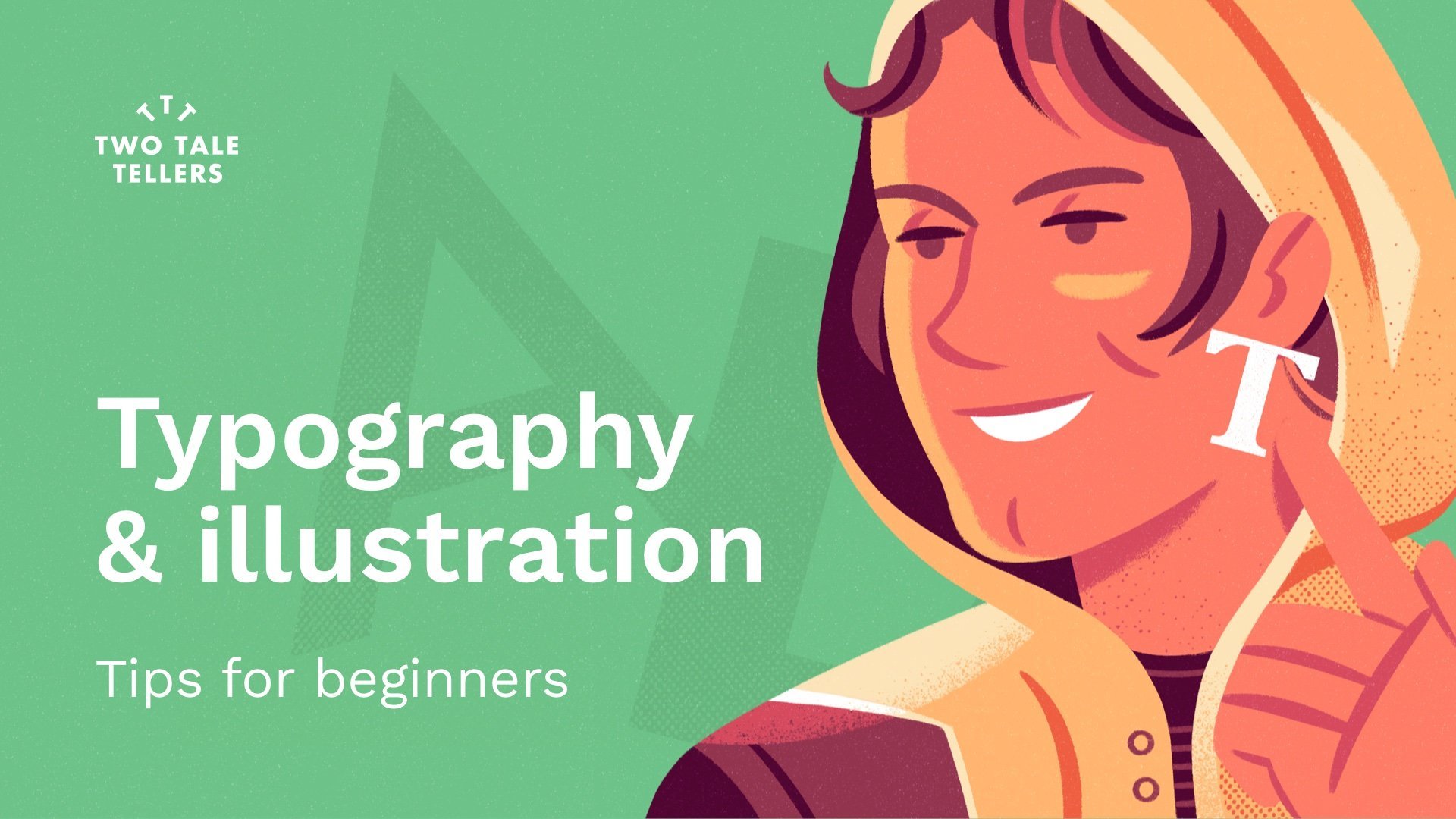
Typographie et illustration : conseils pour les débutants
Avez-vous déjà besoin d'intégrer la typographie dans vos illustrations sans vous sentir exactement celles à choisir ou comment l'utiliser naturellement dans votre travail ? Vous avez été curieux par rapport aux possibilités non seulement fonctionnes, mais aussi en plastique et en matière d'esthétique de typographie ?
Comment les jouer avec la perspective d'un illustrateur ou d'un artiste ? Vous avez vous ressenti un peu intimidé, car il est complexe et en théorie, il est orienté à la conception de graphiques ? Ce cours est pour vous.
Ce est et n'est pas ce
Il ne s'agit pas d'un cours de conception graphique ou typographiques, mais vous en apprendrez un peu plus sur la typographie, comment l'utiliser dans la pratique et en intuition, comment l'intégrer dans votre travail régulier en tant tant qu'illustrateur et comment is dans une perspective graphique.
Ce que vous apprendrez
à la fin de ce cours, vous aurez quelques notions pratiques de la typographie et de nouveaux outils créatifs. Et l'espoir n'hésitez pas à améliorer votre portfolio, vous pouvez relever quelques illustrations nouvelles et intéressantes.
Ce cours est particulièrement s'adresse à :
Illustrateurs qui ont intérêt à apprendre à utiliser la typographie dans leur travail, il est entièrement ouvert à toute créative qui possède un intérêt à la typographie ou à l'illustration.
1. Introduction: Avez-vous déjà eu besoin d'intégrer la topographie dans votre travail sans savoir exactement lequel choisir et comment l'utiliser naturellement dans votre travail, avez-vous été curieux des possibilités, non seulement fonctionnelles mais aussi plastiques esthétiques de typographie. Comment jouer avec eux du point de vue d'un Illustrateur ou d'un artiste, avez-vous été quelque peu intimidé par lui parce que c'est complexe et en théorie orienté vers les graphistes. Dans ce cas, c'est votre classe. Mon nom est le rôle et je suis illustrateur et designer. J' ai travaillé pour des contenus éditoriaux, des marques et des produits, des projets narratifs interactifs , des jeux vidéo et tout support dans lequel des images, des pupilles ou des interactions sont combinées pour raconter Soyouz. Très souvent, je m'adresse à mon travail d'illustrateur. Ma connaissance de la topographie s'obtient après 20 ans travail dans des domaines tels que l'entité d'aide visuelle ou la conception d'interface. Et croyez-moi, ça peut être un excellent outil pour un illustrateur. Ce n'est pas un verre de design graphique ou typographique, mais dans celui-ci, vous en apprendrez plus sur la typographie dans la façon de l'utiliser d'une manière pratique et intuitive. Comment l'intégrer dans votre travail régulier en tant qu' illustrateur et comment l'utiliser d'un point de vue plus graphique. Commencera par donner quelques conseils essentiels pour choisir le bon téléphone en fonction du contexte. D' une manière pratique et non académique. Nous parlerons de différentes méthodes pour l'intégrer visuellement dans votre travail afin qu'il ne semble pas détacher de votre façon de lancer. Ensuite, nous allons proposer trois exercices avec un petit projet associé à chacun que vous pouvez choisir de faire. Tous sont concentrés sur celui qui vous intéresse le plus. Ces exercices vont de l'intégration de textes de base à l'utilisation de la topographie comme élément visuel clé dans vos illustrations. Je vais vous montrer mes propres exemples et ceux d'autres illustrateurs et société Alec que vous créez mes propres projets autour des exercices proposés. Enfin, je vais vous donner quelques références sur l'endroit où trouver des polices de qualité complètement gratuites ou très abordables et quelques conseils finaux. À la fin de ce cours, vous aurez des notions pratiques de typographie, nouveaux outils créatifs et, espérons-le, de nouvelles illustrations intéressantes qui vous permettront d'élever votre portfolio. Pour prendre la classe, vous avez besoin de votre créativité. Les moyens que vous seriez juste de faire des croquis et vos outils habituels tant qu'ils vous permettent de manipuler la topographie, moins d'une manière simple. Illustrator, Photoshop, procréer, Affinity Designer, chacun d'entre eux fonctionnera pour vous. Ce cours s'adresse spécifiquement aux illustrateurs qui veulent apprendre à utiliser la typographie dans leur travail. Mais est complètement ouvert à toute personne créative ayant un intérêt pour la typographie ou l'illustration. Êtes-vous prêt pour ça ? Je suis allé te chercher dans la vidéo suivante. Commençons. 2. Votre projet de cours: Cette classe est divisée en trois exercices qui représentent trois propositions pour explorer la topographie. Pour illustrer chacun des exercices, je vais créer un projet personnel. Je vous invite à développer vos propres projets autour du verre. En tant qu'étudiant, vous pouvez choisir de produire un projet pour son exercice. Oui, choisissez un ou deux, ou même faites plusieurs illustrations pour chaque exercice. C' est complètement à vous de décider. Dans notre exemple de projet, vous pouvez voir comment nous avons présenté nos propositions pour chaque exercice, décrivant leur processus créatif derrière eux, les polices utilisées dans un petit contexte autour de la solution. Vous pouvez utiliser nos projets comme exemple pour structurer les vôtres. Mais bien sûr, vous avez une totale liberté de montrer avec une supernova. Donc, avec le projet clarifié, commençons par le verre et le premier exercice, accompagné de divers conseils, je vous invite à développer vos projets au fur et à mesure que la classe progresse. Ça commence. 3. Exercice 1 - Intégration du texte: Nous commencerons par l'un des contextes les plus élémentaires quand il s'agit de la dorothie appliquée à l'illustration, c'est-à-dire la présence de la topographie dans un texte. Ce texte peut être mordre un morceau de journal, un panneau dans une rue, un dessin typographique sur un t-shirt de personnage, textes sur une carte illustrée, etc. Voyons quelques exemples. Parfois, ces textes peuvent avoir une présence très limitée dans votre travail. Comme dans cette illustration faite pour un article sur Medium. Comme vous pouvez le voir, certains petits textes, tels que la plaque d'immatriculation, sont parfaitement intégrés dans l'illustration. Et malgré sa subtilité, ils fournissent la crédibilité nécessaire à ce petit composant visuel mal traité pourrait avoir un impact vraiment négatif sur l'ensemble. Dans cette autre illustration, nous adaptons la police au contexte lié à protéine avec la police Meghan ou égyptienne qui s'adapte au flux du dessin. Dans l'autre, nous pouvons voir comment la topographie s'adapte à la construction de l'illustration, s'y intégrant et en délivrant un message en même temps, ce qui renforce le résultat général. Dans cette belle illustration de la grande carte de l'artiste, nous pouvons voir comment il a intégré ce panneau dans le bâtiment avec un choix typographique intelligent et une finition précise pour son contexte. Steve offre comme d'innombrables exemples sur la façon intégrer professionnellement la topographie dans son travail d'illustrateur en utilisant pratiquement toutes les méthodes d'intégration décrites dans la vidéo 5 de son verre. Eh bien, je vous ai parlé de la façon d'utiliser le type d'une manière qui ne semble pas hors de propos compte tenu de votre style personnel. Souvent, le peu de soin dans le choix de la police et le manque d'intégration visuelle dans l'illustration, même dans des contextes professionnels, rendent les résultats quelque peu maladroits et ne disent pas grand-chose sur la garderie pour la finition de sortie pour cette raison, avant de commencer notre premier projet, nous allons voir quelques conseils sur le choix et utilisation de la typographie sans entrer dans trop de détails techniques. L' indention est de faciliter l'utilisation de ces ressources pour les personnes qui n'ont pas une formation spécifique en design graphique générant malgré cela, un bon résultat final, partons avec nos premiers pas, qui seront très utile dans tous les exercices de la classe. 4. Exercice 1 - Conseils de choix typographiques: Choisir la police correcte représente probablement 70 % du travail. Le choix de la police est quelque chose de vraiment subtil et nécessite une connaissance de jugement. Comme d'habitude, plus nous en savons sur la typographie, il est facile de la subvertir. Utilisez un graphiste professionnel expérimenté à bonne maîtrise utiliser une base de données apparemment inappropriée pour un contexte. Mais partons de la prémisse que nous n'avons pas une formation spécifique et ignorer que voir quelques cassettes à la loi plus rapidement par le brouillard est notre choix. Considérons au moins trois aspects. Un, contexte général à la nécessité fonctionnelle, trois propriétés esthétiques. Regardons quelques exemples et analysons chacun des points qui y sont mentionnés. Revenons à l'illustration précédente de Steve Scott. Pensons à l'éclatement du contexte général. Nous parlons d'un hôtel élégant et sophistiqué avec une touche traditionnelle. Il semble tiré d'il y a quelques décennies. Logiquement, cette situation n'exige pas une déphase punk informelle, jeune et audacieuse, bien au contraire. Elle exige une certaine souveraineté et une certaine distinction. En étant conscients de cela, nous aurons commencé à nous concentrer sur notre choix. Besoins fonctionnels dans ce cas, R est dominant. Nous parlons d'un grand panneau visible et nous avons seulement besoin du nom de l'hôtel pour être lisible. Et même si elle n'était pas totalement lisible, cela n'affecterait pas la perception générale de l'illustration. Enfin, considérons les propriétés esthétiques. Quel type de police exige-t-elle une telle situation ? Une police de caractères extraterrestre aurait pu être un choix approprié. Mais ici, Steve utilise un friand avec quelques souvenirs historiques contemporains qui offre le bon degré entre modernité et tradition pour contraster avec la main, les finissent par fournir une belle finition finale. Passons à une autre affaire. Ici, nous voyons comment la lame de licence en arrière-plan reçoit toute la tension typographique dans l'illustration. Dans ce cas, un contexte général et un besoin fonctionnel. Clair. Nous parlons d'une plaque d'immatriculation, et la grande majorité des plaques d'immatriculation dans le monde ont une apparence similaire en termes de topographie. La raison est simple. Nous parlons généralement de la police OCR. C' est le signe de la reconnaissance optique des caractères. Clairement lisible, reconnaissable et scannable, sorte qu'il est impossible de confondre certains personnages avec d'autres. Même si cette police n'est pas celle utilisée dans les plaques d'immatriculation. Il répond à toutes les exigences en termes de contexte, de fonction et d'esthétique, sorte qu'il est perçu comme crédible que leur biographie pour New York est beaucoup plus libre et fournit simplement un contraste avec le numéro de plaque d'immatriculation. Le contraste qui est produit non seulement en termes de style, mais aussi en échelle, poids et couleur, séparant clairement les deux chauves-souris. Et comme un k supplémentaire, nous pouvons étudier comment dans ce jeu vidéo que j'ai aidé à concevoir les choix typographiques, réagissant aux points décrits avec une relation esthétique évidente. Triple Squad était un jeu très simple et puissant. Tous les éléments du jeu où l'édition minimaliste et compacte ou coeur et la police monospace à la recherche mécanique ont été utilisés pour la construction du logo et du texte de soutien. Les véhicules du jeu semblaient avoir été conçus à côté de la police. Il y a une esthétique ou une relation évidente. Fonctionnellement, Arete a été relégué à court un texte d'impact. Enfin, nous pourrions considérer le budget comme le quatrième à examiner. Avoir le budget à acheter. typographie peut multiplier vos possibilités, bien qu'elle ouvre également un immense espace. limiter aux polices accessibles vous aidera à vous concentrer sur les options disponibles, même si vous devrez peut-être sacrifier l'accès à de meilleures alternatives. Rappelons-nous encore une fois, soyons logiques compte tenu du contexte général. Pesons le besoin fonctionnel de cette police à quel point C'est Bertha qui crée nécessaire. Examinons ce que nous voulons que cette police de caractères exprime ? Autrefois sérieux, gentillesse, fraîcheur, parallèles ascétiques avec le reste des éléments de l'illustration, etcetera. Voici quelques conseils généraux pour vous guider dans ce premier choix. Nous en verrons plus à ce sujet dans l'exemple de projet. Mais une fois ce choix fait, il est temps d'utiliser cette RFI dipôle dans l'illustration. Comment l'intègrons-nous ? Comment l'utiliser de telle sorte qu'il ne se sent pas d'un monde différent de votre illustration ? Voyez quelques conseils pratiques dans notre prochaine vidéo. 5. Exercice 1 - Conseils d'intégration: Si votre travail est formellement simple, plat et principalement vectoriel, vous n'aurez pas trop de problèmes puisque la finition Buffett de la topographie s'adaptera parfaitement à vos illustrations. Si d'un autre côté, vous avez un style plus organique, cette topographie pourrait sembler hors contexte comme un mais quelque chose de super-imposé sur le net. Et cela appartient à un monde différent, peu intégré. Je vais donc recommander trois méthodes différentes pour faire l'intégration. Un, la manipulation numérique, au redessin, et trois, l'imitation. Laissez expliquer très rapidement ce qu'ils consistent en utilisant quelques exemples. Manipulation numérique. C' est l'une des options, sont utilisés le plus dans mon travail, mais il nécessite une compétence à manipuler numériquement la topographie. L' intention est de déformer ou d'éroder numériquement les lettres afin que nous obtenions une finition artificielle proche ou au moins compatible avec nos illustrations. C' est exactement ce que j'ai fait dans cette illustration qui parle nomades et des gens qui ont littéralement porté leur maison dans leurs circuits. La présence de textes est subtile et peu pertinente dans l'illustration, mais son intégration est adéquate. Regardons la finition de la police de caractères. La même chose se produit dans ces autres illustrations. Nous voyons que la topographie, malgré le maintien de toutes ses caractéristiques d'origine, est légèrement déformée de sorte qu'elle s'intègre plus naturellement. Dans mon exemple de projet. Dans la vidéo suivante, je vais vous montrer comment nous pouvons faire ce type de modifications à l'aide de Photoshop. Regardons la deuxième possibilité lors de l'intégration de la topographie, du redessin. Il consiste littéralement à utiliser la police correspondante dans votre composition. Et il suffit de le redessiner en utilisant vos brosses et finitions habituelles. Comme vous pouvez le voir dans ces illustrations que j'ai faites il y a quelques mois pour le jeu vidéo, Threadless Trail of blood. Le texte semble être une typographie simple disposée sur l'illustration. Mais si on se rapproche de leur détail, on verra que la finition des lettres est exactement la même que le reste de l'illustration avec toutes ses imperfections. Essentiellement, notre main a tracé le design parfait d'une police à la main. Nous pouvons voir le même processus dans la topographie organiser sur le T-shirt de ce personnage du même jeu vidéo. Ou sur la dernière petite note dans cette histoire officielle courte et structurée. Le résultat est que nous conservons toutes les vertus et les caractéristiques de la police d'origine, mais légèrement subverties par notre propre processus de travail créant une intégration remarquable. Évidemment, cette option nécessite beaucoup d'efforts et elle n'est recommandée que pour de petites interventions typographiques. Voyons une autre façon d'intégrer la topographie, très utilisée par les illustrateurs et l'imitation. Nous avons une alternative que nous pourrions déjà envisager le lettrage, car cela implique d'imiter manuellement l'apparence d'une police. La différence avec le redessin est que, dans ce cas, nous n'avons pas besoin d'avoir une référence pour en tirer parti. Nous interprétons manuellement l'attribut d'une police en fonction de notre besoin. Généralement, le résultat finit par être une police de caractères qui s'est déjà éloignée de la référence d'origine, mais qui conserve largement son identité. Nous pouvons voir quelques exemples pourquoi matériel don Noter comment il imite une police condensée sans serif sans être reconnu comme personne en particulier. Vous dessinez essentiellement des lettres, donc celles-ci s'adaptent parfaitement à vos illustrations. Voici un exemple de Steve Scott ce qu'une police de caractères rappelle plusieurs polices similaires sans être réellement aucune, car elle imite l'aspect approximatif de la police ici nécessite. Alors rappelons-nous, le choix d'une police appropriée est une décision importante. Les deux. Donc E l'utilise correctement dans son contexte. Les aspects fonctionnels sont souvent au-dessus de l'esthétique, mais les cas brillants sont ceux qui établissent un juste équilibre entre les deux. Et l'utilisation originale et intéressante de la typographie peut devenir un élément identitaire important dans votre projet. Avec cette information entre nos mains, nous allons commencer à résoudre notre projet pour ce premier exercice. se voit dans la vidéo suivante. 6. Exercice 1 - Exemple de projet: Maintenant que nous avons le contexte complet de son exercice, je vais commencer par mon projet d'intégration typographique. Je vous invite à vous joindre à moi. Ce sera assez bref puisque nous allons nous concentrer sur la typographie en durée sur une illustration prête à l'emploi. Laissez-le commencer par un exemple très simple, qui peut nous aider à nous réchauffer puisque la police serait appliquée sans trop d'autres Asiatiques en perspective, va commencer à partir de cet exemple, une illustration secondaire pour un qui parle de l'importance des couvertures de livres. L' illustration fait allusion au fait que la couverture, en particulier dans les œuvres autopubliées, devrait parler de l'autre. Votre identité ou votre image personnelle devrait atteindre la couverture. Nous l'exprimons à travers un dessin dans lequel, euh, la couverture et la phase sont les mêmes. Maintenant, nous devons itérer en textes, titre et autres, bien que les deux soient très génériques. Donc on va résoudre ça avec mon roman et le nom et Smith. Maintenant, nous avons besoin d'un peu de contraste entre les deux textes. Et il y a plusieurs façons d'obtenir ce contraste. Cela peut être à travers une différence dans le poids du type, phase, la différence de taille, la différence, couleur, la différence de style, ou plusieurs de ces possibilités en même temps. Nous commencerons donc par expérimenter diverses combinaisons. Dans ce premier exemple, le contraste est quelque peu exagéré. Bien que le texte rappelle la machine à écrire monospace dans les polices, il est très mince et serait probablement perdu dans la conversation. D' autre part, le titre est un peu générique en termes de style. En inversant les styles, nous n'obtenons pas un résultat particulièrement intéressant. Essayons de changer la police du titre en une avec serif. Honnêtement, je l'aime mieux. Il a plus de caractère. Mais un contraste avec la police à espacement unique ne m'a pas convaincu. Rappelez-vous que nous n'avons pas besoin d'utiliser différents styles. J' utiliserai le même formulaire pour le nom init Alix et en respectant la différence de tailles. Pas mal. Peut-être si c'est classique. Ok. Retournons en arrière. Que diriez-vous d'utiliser une police sans serif ? majuscules avec un certain poids. Je l'aime, mais je pense que je vais envisager d'utiliser la même police pour les deux textes comme nous l'avons fait avec la police serif précédente. Je pense qu'il y a deux options sont certainement les plus intéressantes. Allons donc à Photoshop et je vais vous montrer comment nous appliquons ces fonds à l'illustration originale en utilisant la première méthode d'intégration décrite dans la vidéo précédente. N' oublions pas que le processus précédent est une version simplifiée et simple de ce qui serait un processus beaucoup plus organique et parfois rigoureux. Prenez le temps dont vous avez besoin pour étudier les possibilités. Une fois que nous sommes dans Photoshop, Nous allons commencer par entrer le texte nécessaire pour séparer les zones de texte pour être en mesure d'être manipulé indépendamment. Positionnera chaque zone de texte à peu près sur l'illustration. Ensuite, nous allons appliquer la couleur à chacun pour donner la palette de couleurs est un plus petit possible. Nous utiliserons l'un des verts pour le titre et le blanc pour le texte inférieur, qui contrastera suffisamment, changera la taille et le poids pour le rapprocher de l'aspect final que nous avons choisi dans notre étude précédente. Et après cela ferait pivoter les deux zones de texte 15 degrés, qui était un TLT utilisé pour faire pivoter le livre dans l'illustration. Et une fois qu'une décision est à nouveau ajustée, notre première proposition est présentée. Comme vous pouvez le voir, la finition imparfaite de l'illustration est différente de celle d'une police qui conserve son design parfait intact. Cela rend la topographie mal intégrée, évidemment superposée sur le dessin. Plus tard, nous appliquerons un ajustement. Évitez ce remplissage et améliorez l'intégration. Passons maintenant à notre deuxième proposition. L' utilisation de la police sans serif choisie précédemment appliquera la manière appropriée à chaque texte, positionnera chacun d'eux là où ils appartiennent. Dans le cas du nom de l'auteur, nous allons réduire sa taille et augmenter l'espace entre les caractères. Et le moyen facile de le faire est en sélectionnant les ponts et en appuyant sur l'option plus la flèche gauche ou droite pour l'augmenter ou la diminuer. Et avec cela, nous avons nos deux propositions, le temps de choisir. Comparons les deux. Bien que les deux semblent adéquats. Il me semble que dans ce cas, la police serif est un peu classique pour le style graphique de l'illustration. Et bien que cela puisse donner lieu à un contraste intéressant, je pense que dans ce cas, j'opterai pour une proposition moins contrastée. Après tout, la topographie est ici un élément complémentaire avec une décision prise il est temps d'améliorer l'intégration visuelle de la typographie. Pour ceux-ci, j'utiliserai Photoshop pour modifier les barons de la police. Tout d'abord, je vais sélectionner les deux textes et les transformer en un objet intelligent qui me permettra d'appliquer des effets sur la typographie de manière non destructive. L' une des choses qu'ils utilisent le plus dans ce cas est le filtre d'ondulation, qui est légèrement déforme les contours, les rendant moins parfaits sont plus organiques. Dans ce cas, il s'agit de jouer avec la taille et la quantité de défaut. Heureusement, faire une erreur ne sera pas un problème. Nous pouvons changer les paramètres autant que nous le voulons. Nous allons pour une taille plus petite, plus subtile, et une quantité d'effet plus faible. Si nous zoomons, nous pouvons voir comment la démographie semble être un peu plus proche de la fin de l'illustration. Peut-être que le défaut est invisible lors du zoom arrière. Donc nous allons forcer le social dans un peu plus. Nous allons éditer le petit filtre et changer les paramètres. Puisque l'illustration a une texture subtile ou appliquée, améliorera la sensation d'être imparfait textes imprimés en masquant le dx avec une certaine texture. Si vous regardez le détail, vous verrez à quel point le texte semble faire partie de l'illustration d'une manière naturelle. Observez un petit détail. ce moment, nous travaillons à la plus grande taille que celle que nous trouverons à utiliser. Nous allons donc copier le contenu du fichier. Nous allons le coller dans un autre document. Et nous allons réduire l'échelle à 50%. De cette façon, nous pouvons voir la finition finale jusqu'à la réduction de l'image. Beaucoup de détails qui peuvent sembler quelque peu artificiels sont devenus beaucoup plus naturels et il est difficile de savoir comment cette police a été appliquée pour paraître si bien intégrée. De cette façon, j'ai déjà intégré ces petits textes qui ont fini par faire partie de mes illustrations. D' une part, la police choisie semble appropriée à son contexte. L' intégration avec un léger autre angle de rationnement est assez crédible. La légère déformation pour éviter la finition mécanique des personnages ainsi qu'un effet de détresse ont contribué à l'intégrer sur l'illustration. Concernant les facteurs importants. Premièrement, un bon choix typographique basé sur les conseils que nous avons vus dans notre vidéo précédente plutôt qu'à un traitement et une intégration adaptés à la nature de votre travail. Et j'espère que de cette façon, ajouter un petit texte intégré sur vos illustrations sera un peu moins intimidant de la part de personne. Allez-y et préparez et partagez votre projet pour cet exercice. Si vous vous sentez particulièrement courageux, offrez-vous un défi intéressant, comme avoir à itérer un texte d' importance notable dans le contexte de votre illustration. Passons maintenant à un deuxième exercice. Cette fois beaucoup plus axé sur la valeur plastique de la typographie. 7. Exercice 2 - La typographie comme cadre visuel: Dans cet exercice simple et amusant, nous allons voir comment la typographie peut être utilisée à d'autres fins, plus proche de la conception graphique, l'objectif est que l'exercice vous inspire à faire plus de recherches sur la topographie et à l'utiliser dans un façon plastique. Nous choisirons un concept que nous sommes intéressés à représenter. Cela peut être un remplissage, une couleur, ce pays, un genre musical, tout ce qui peut être illustré et que nous pouvons identifier avec le mot. Ensuite, nous allons utiliser le type 4f0 pour créer un élément visuel pour encadrer notre illustration. Il peut s'agir d'une seule illustration ou d'une illustration pour chaque personnage unifié de façon spectaculaire. L' idée est que la topographie renforce le caractère du concept illustré. La chose la plus simple sera de voir un exemple clair. Je vous invite à suivre mon propre processus afin que vous puissiez voir comment je crée cette petite composition typographique illustrée étape par étape. Allons-y. 8. Exercice 2 - Exemple de projet: Pour cet exercice, j'ai cette édition pour utiliser le concept de Noé, une erreur mal définie, qui couvre un bon nombre de thèmes et si généreux que j'aime. Donc, je vais dépeindre divers stéréotypés, puisque dans chacun des caractères du mot, commençons par le début. Un peu de recherche. Selon le thème choisi, vous aurez besoin de plus de références que dans d'autres. Dans mon cas, je vais faire une brève recherche sur le non-genre, surtout pendant les années 40 et les vainqueurs. Si nous n'avons pas de recommandation directe, nous pouvons faire des recherches sur internet, en particulier dans le domaine cinématographique. J' ai pu trouver de multiples références sous forme d' affiches et aussi dans le graphisme utilisé dans les productions elles-mêmes. Je dois dire que le traitement typographique de ces années est étonnamment atteint. Mais nous pouvons voir comment certains modèles se répètent dans la plupart des productions de la NWA en raison du besoin d'espace. Et beaucoup de ces itérations que les polices utilisent ont tendance à être condensées et généralement lourdes pour fournir un contraste évident. Ils ont également tendance à être des fonds grotesques sans droits de douane, forts, solides. Et donc nous sommes des fonds pas très émouvants. Nous allons le résumer dans le colorant besoin condensé, faux et compacts. Des centaines de polices qui répondraient à cette description. Mais je ne considérerai que ceux qui sont à ma disposition et qui alimentent le besoin identifié. Si vous n'avez pas d'options qui répondent à vos besoins. vidéo 11 de cette classe, je vais vous offrir quelques ressources qui vous aideront à trouver l'unité de polices. Avec ces contextes rap, les options sont réduites et nous pouvons nous concentrer beaucoup mieux. Nous connaissons ce genre de topographie dont nous avons besoin. Et maintenant, il s'agit de comparer certains et de blâmer avec eux. Eh bien, ma sélection serait à peu près ceci. Comme vous pouvez le voir, certaines options répondent aux contextes identifiés, mais peut-être qu'ils sont à moderne comme Avenue ou t-star ou excessivement érodé comme Vn route. Bazaar est peut-être le téléphone avec lui hébergement Mozart est statistiquement lié à des articles, signes du milieu des années trente. Cependant, il partage une particularité avec Garrett Gothic. Il est assez mince et l'espace intérieur disponible pour placer l'œuvre est un peu petit. Donc on va opter pour le knock-out. Une belle famille avec un design classique et de caractère complet, qui a également une multitude de poids. Nous pouvons même nous permettre de l'augmenter pour atteindre une plus grande masse typographique. À ce stade, nous avons terminé avec la première étape de cet exercice. Mais si vous avez envie de jouer un peu plus, peut-être que nous pouvons aller un peu plus loin ce premier choix typographique. Encore une fois, nous connectons un élément cliché comme un pistolet à la composition typographique. Essayons. Tout d'abord, nous allons taper le mot que j'utilise une Australie pour ça. Je vais dupliquer dans la zone de texte et utiliser le second pour taper un couple de commerce et long tiret. Ensuite, nous allons convertir tout le texte en formes pour ne pas les contrôler librement. Vous pouvez voir comment nous avons perdu cette capacité d'édition de decks, mais maintenant nous pouvons jouer avec les personnages indépendamment. Tous les jours. Le, oh, donc c'est plus long et on ne l'a pas utilisé pour créer notre pistolet typographique. Ensuite, je commence à espacer tous les éléments et bougerais le bras pour créer la poignée. Et maintenant, le commerce fonctionnera comme un déclencheur et le marteau. Et nous avons un pistolet très abstrait, qui est encore lisible. Pour augmenter la tension visuelle fera pivoter toute la composition 15 degrés. Et le voilà. Après cela, nous pouvons exporter notre composition où nous avions besoin Photoshop, procréer, ou rester dans Illustrator si c'est l'application que nous utilisons habituellement, vous pouvez deviner, sont exportés fichier PNG et sans importance dans la procréation. Nous avons donc réussi à transformer cela en ceci sans perdre notre travail dans la RNF. Maintenant que nous avons la base de notre illustration, il est temps de commencer à dessiner. Ça pourrait commencer par quelques croquis. Là. Je vais passer au processus de dessin réel et ensuite j'appliquerai le choléra en utilisant la procréation. Allons l'entendre très vite. Alors décidons de ce que nous pouvons dessiner dans chacun des personnages. Je pense va jouer avec les stéréotypes. Comme le détective classique, l'URL modèle classique, et le classique ne réglage de films noirs et romans. Décidons comment les séparer tous. Je vais positionner l'inspecteur et la femme fatale dans les personnages opposés , comme s'il y avait une relation tendue entre eux. Donc nous avons l'inspecteur devant la dame. Et maintenant, nous devrions décider quoi utiliser dans le reste des personnages. Peut-être des balles ou des cigarettes et une petite boîte d'allumettes. Peut-être pourrions-nous éviter une cigarette à l'intérieur de la virgule et faire la fumée plus tard. Donc, nous avons ces caractères très différents, sévères. L' un d'eux est blanc et l'autre très vertical. Peut-être que nous allons sentir le I avec quelques détails d'une ruelle sombre avec une lumière de rue. Et utilisez le o pour présenter une voiture des années quarante ou cinquante. Ou on pourrait les relier tous les deux. Donc ils montrent une seule scène reliant la voiture et le début. Donc ça ressemble à un plan. Faisons-le. Nous allons commencer par importer notre type de composition ethnique et l'utiliser comme base afin que nous puissions voir les limites de chaque personnage et commencer à laisser tomber tous les éléments importants dans différents, car nous ne dépenserons pas beaucoup temps avec les détails. Commençons à définir les grands éléments et nous y reviendrons plus tard. Dessinons la balle ne ferait qu'un, puis la répliquer en utilisant différents angles. Comme toutes les balles ressemblent, rendons les choses plus faciles pour nous. N' oubliez pas de nommer vos calques. Revenons à la cuisine, dessinera quelques lignes horizontales, puis les déformera pour simuler et en perspective. Ces lignes fonctionneront comme guides pour notre chat afin que nous puissions le modifier pour mieux s'adapter à l'ONG. Maintenant va faire le reste des détails à l'intérieur de l'œil. Construisons le pont en dessinant des notes sur les lignes ici et là. Et la boîte d'allumettes, qui devrait être assez simple et directe. Et enfin, notre femme fatale. Essayons un chapeau et des coiffures jusqu'à ce qu'on en trouve les bons. Ok, changeons l'expression qui rend l'hostile beaucoup plus simple et formel, amorphe, spécial, il semble, semble mieux pour le personnage. Maintenant, la clause élégante et simple, qui a également fait l'avait beaucoup plus grand. Donc on fait partie de sa beauté, ce qui la rend plus mystérieuse. Donc, nous avons enfin fini notre promenade de la baie. temps pour la couleur utilisera notre palette réduite de levage bleuâtre et un peu de pain. Tout d'abord, j'ai tendance à faire un S super enveloppé avec un pilote pour voir si cela fonctionne. Tu n'as pas à passer beaucoup de temps avec ça. Une fois que vous avez terminé, nous pouvons commencer à colorier la pièce finale. Généralement, je commence à faire les appartements, essentiellement les principales masses de couleur définissant les éléments importants de la scène. Cela prend généralement du temps, et c'est important car ces formes définissent l'illustration à de nombreux niveaux. Une fois que nous avons ces formes d'inondation, nous pouvons commencer à ajouter ici des extraits définissant les détails de Tom , les textures, le volume, etc. Comme vous avancez, votre probablement improviser beaucoup avec certains des détails et l'utilisation de votre propre palais. Ne vous inquiétez pas si vous avez besoin de repenser certains Merci à ce stade, tant que vous respectez votre dessin précédent, qui définit votre chemin tout le temps. L' utilisation de la palette de rayon est génial parce que parfois vous avez besoin de trouver des solutions intelligentes à des situations spécifiques. À cause de vos propres limites. On y est presque. Définissons un peu le caractère final. Plus de détails, et c'est fini. Donc nous avons nos apparences faites, mauvaise surprise, surprise. Une fois terminé, j'ai décidé de prononcer la palette entière en utilisant une palette moins contrastée et plus rouge ou une moins vibrante mais plus élégante. Ces choses se produisent si vous avez été méthodique lors de la structuration de votre fichier, cela n'a pas à être problématique. Les médias numériques offrent une grande flexibilité. Heureusement, à partir d'ici, vous pouvez même vous encourager à animer les éléments contenus dans les connecteurs typographiques pour donner vie à cette petite fenêtre dans votre chaleur illustrée. C'est ton tour. Faites vos propres recherches et commencez à créer votre base. Vous pouvez être aussi simple qu'une guerre dactylographiée, en utilisant la topographie PA supérieure ou aussi complexe qu' une composition typographique libre, puis introduire ces illustrations pour générer des bières finies. Prenez la détention, vous avez besoin de police n, partager les résultats lorsque vous êtes prêt. Nous passerons au troisième exercice dans lequel nous utiliserons la typographie d'une manière légèrement différente. Notre largeur pour vous dans la prochaine vidéo. 9. Exercice 3 - Typographie en tant qu'élément graphique: Dans cet exercice, nous allons vraiment jouer avec une biographie. Nous allons briser ces mots, séparer leurs caractères si vous le souhaitez, et les transformer en objets qui auront du poids, une entité dans votre illustration, nous allons essayer de traiter les lettres comme des éléments graphiques. A cette occasion, qu'ils ont acheté du café devrait avoir notre valeur communicative aussi, mais ce n'est pas nécessaire. Cela va chercher une lecture textuelle. Regardons quelques exemples. Dans cette illustration de mon collègue et ami McGautha, illustrateur super talentueux, nous pouvons voir comment l'exclamation agit comme le dos de la montagne. Se transformant en une question Mike, avec les grappes. Une façon brillante d'intégrer la topographie et l'illustration dans un but communicatif et esthétique à la fois. Dans cette illustration qu'ils ont faite pour illustrer le passé sur les mantras pour les écrivains, nous voyons comment certains caractères typographiques flottent parmi les autres objets qui entourent l'écrivain. Dans ce cas, les lettres deviennent des éléments qui font partie des personnages vivent et se comportent comme des objets physiques. Dans cette autre illustration par Steve Simpson, Nous voyons comment son fait usage de la typographie pour créer un volumétrique 50 qui est une partie essentielle de l'illustration tout en intégrant de nombreux autres textes comme nous l'avons vu dans notre premier exercice, dans un vibrant, de manière insouciante et visuellement cohérente. Et ici, nous pouvons voir un morceau par les toujours asylees pour voir Dasani matin, dans lequel certains personnages agissent comme des éléments presque architecturaux. Je vous recommande de jeter un oeil à l'un des plus beaux projets Cimon impliquant la topographie. Et précisément, vous pouvez voir comment tous ces beaux personnages ont partagé les espaces avec des personnages typographiques qui se comportent comme des objets physiques. Un projet beau et inspirant pour les amoureux, moitié topographie et illustration. Alors, tout d'abord, pensez au concept essentiel de votre illustration. Comment ces personnages vont faire partie de votre composition. Comment interagiront-ils avec le reste des éléments ? Avant de passer à autre chose, passez autant de temps qu'il vous faut pour faire toutes les esquisses nécessaires à la définition de votre concept. S' est joint à moi dans mon projet pour cet exercice, et peut-être ceux-ci vous inspireront un peu pour créer le vôtre. se voit dans la vidéo suivante. 10. Exercice 3 - Exemple de projet: Eh bien, et nous voulions développer mon projet autour cet exercice à faire est que je commence par mélanger quelques idées et il verra celles que nous pouvons développer ce genre d'idées aléatoires. Je vais faire des élections très rapides afin d'illustrer le processus. Mais s'il vous plaît, prenez votre temps et développez vos propres concepts autant que vous le souhaitez. La première idée pourrait être d'utiliser le mot sport comme élément physique dans la scène, dans lequel chaque personnage pourrait faire une sorte d'activité en utilisant les personnages. Par exemple, quelqu'un sautant à travers le gymnaste O. A utilisant le T comme obstacle, ou transformant le S en tableaux avec des gens en cours d'exécution. La deuxième idée pourrait être de se concentrer sur les personnes portant des accessoires typographiques, par exemple, des pendentifs, des boucles d'oreilles, et d'autres choses que nous pourrions trouver. Peut-être pourrions-nous rendre ces caractères plus évidents en utilisant une distinction claire de couleur. Une autre chose. On pourrait l'essayer comme dessiner un personnage supportant le poids d'une série de caractères typographiques. Ce serait cool si les caractères formaient le bon mot conceptuellement. Par exemple, la vie. Nous pourrions expérimenter différentes façons d'afficher les mêmes scènes. Donc je vais choisir cette dernière option, mais je pense qu'on pourrait faire quelque chose d'intéressant avec l'autre. Finalement. Une fois que nous sommes clairs sur ce concept général, il est temps de commencer à résoudre l'illustration. Encore une fois fera une tournée à la phase de dessin, coloration, et enfin, l'intégration typographique. Donc, nous allons faire une personne très moyenne, quelqu'un travaillant dans un bureau, portant un costume et une mallette, et expérimentant le poids de la vie, littéral et conceptuel. Commençons par dessiner le personnage principal. On peut commencer à ajouter des compliments comme la mallette, pour que ça se sente plus légaliste et banale. Si vous utilisez la procréation. La fonction de longueur rapide est vraiment intéressante pour créer un élément plus inorganique. Et pour créer une ombre était juste faire quelques cercles, puis unir les deux formes en effaçant les lignes inutiles. Allons maintenant au deuxième bras, va essayer de le définir et de le repositionner un peu. Ajoutons un peu de volume aux vêtements lorsque nous colorions, il utilisera un motif visuel pour l'intérieur de la veste. Et maintenant que nous avons le Canada principal, nous pouvons jouer avec lui, des lettres, essayer d'imaginer différentes dispositions. Bien que nous allons faire cela dans Photoshop essayant d'imaginer maintenant comment nous pourrions utiliser la déformation, la rotation, ou les jeux, ces caractères seront très utiles à le faire maintenant ne nécessite pas beaucoup de temps et de précision, et nous allons enregistrer un beaucoup de temps plus tard. Alors allez fou et imaginez autant de scénarios pour la typographie que vous le souhaitez. Certains d'entre eux se sont accumulés dans une disposition verticale, certains d'entre eux dans un plus de blocs de distance. Cela définit déjà vos choix typographiques. Eh bien, l' une des choses que nous avons est que le dos du personnage est fondamentalement descendant. n'y a donc pas de phase solide pour positionner les caractères topographiques. Plus de test. Cette partie est un bon exemple de toute la pensée visuelle que personne ne voit dans le travail d'une autre personne. Et cela implique parfois des heures de travail. Mais bien sûr, ils sont nécessaires pour arriver au résultat final. Parfois, les clients chose, Notre travail est créé spontanément immédiatement sans méditation sous l'illustration simple comme celle-ci, devrait être fait immédiatement. Si tu peux faire ça vite. C' est juste parce que tu es vraiment habile. Mais ça doit jouer en ta faveur. Donc, nous ne travaillerons jamais sur une base de temps. Mais sur la valeur. Après avoir expérimenté quelques couleurs, c'est notre test de couleur rugueuse, et nous allons l'utiliser pour créer la pièce finale. Nous allons placer notre personnage, définir le calque pour qu'il se multiplie, puis mettre à l'échelle autant que nous en avons besoin. Pour le moment. On va ignorer la topographie. Encore une fois pour générer les masses de couleurs principales. C' est le même coup dessiné 20 fois d'affilée. C'est arrivé. Il est difficile d'obtenir le bon qui se sent naturel, spontané, et qui respecte la ligne d'origine. Vous pouvez aussi appeler nos masses sans précision , puis effacer la partie dont vous n'avez pas besoin. Allons maintenant au visage et aux cheveux. Et maintenant les chaussures. Les petits éléments comme celui-ci sont généralement plus détaillés. Mais n'en faites pas trop. Ce qu'il ressentira hors de propos. Vous devez obtenir un juste équilibre dans le contexte général. Quelques traits finaux ici sous quelques détails à l'intérieur d'un élément. Et enfin, le motif textile pour notre veste. Nous allons utiliser un très classique, puis masquer tout le tempsde composition temps maintenant pour exporter le fichier et l'ouvrir dans Photoshop. Nous pouvons donc commencer à jouer avec une composition typographique en vinyle. Nous commencerons avec celui-ci qui se sent élégant, mais peut-être pas trop lourd. Donc, ça n'aide pas beaucoup sur le plan conceptuel. Même si je l'aime visuellement, je vais dupliquer toute la composition et les déciles minuscules. Peut-être qu'un sans-empattement plus lourd aidera. Spécialement, nous mettons un personnage sur l'autre. Cela donnerait une illustration très pratique, ce qui n'est pas mal. Considérant que nous n'avons pas de mémoire initial d'un client. Essayons maintenant une police serif. Ça apporte définitivement quelque chose à l'ensemble. C' est chic, élégant, sérieux et lourd. Que faire si nous utilisions différentes tailles de police ? Essayons quelque chose de différent. Qu' en est-il d'une police mécanique à espacement unique ? Il se sent comme des blocs métalliques, ce qui est très brut et puissant. Pas cette ordure ton instinct. Oui, utilisez vos ressources et laissez vos yeux vous dire ce qui se sent mieux dans le contexte. Vous n'avez pas besoin de chercher une police spécifique, juste pour un sentiment spécifique. Rappelez-vous la vidéo pour lors de la sélection d'une chose de police du contexte, le besoin fonctionnel, et les propriétés esthétiques. Dans ce cas, nous avons besoin de la police pour se sentir solide, lourd, et nous avons certainement besoin de lire le mot pour comprendre le concept. lisibilité est donc importante dans celui-ci. En ce qui concerne l'ascèse, nous avons plus de liberté dans ce cas. Tout ce qui ne se sent pas à sa place fonctionnera. Bien que nous ayons un personnage qui était très spécifique, proche, légèrement obsolète, peut-être un choix classique pourrait être intéressant. Donc enfin, mes amis, après tout ce processus, nous finissons par utiliser un gros, lourd, solide formé en italique avec sérifs agressifs qui semblait être arrêté dans le dos de ce pauvre homme. La vie semble être difficile pour notre ami. Et en tant que lieu, j'ai expérimenté un troisième concept utilisant des phases de jeunes avec des styles différents. Nous n'avons pas de caractères typographiques, une sorte de complément. Et entendre des lunettes de soleil abandonnées et une épingle à cheveux. Et nous les utiliserons pour présenter chaque vidéo en verre. Donc double projet pour cet exercice. Et maintenant, c'est ton heure. Ne pensez pas nécessairement aux interactions entre les polices de caractères et les caractères. Ces caractères typographiques pourraient être des objets dans un paysage qui pourraient composer un ensemble et Fieger entre eux. Ils ne pouvaient pas contenir de texture et d'attributs volumétriques. Sentez-vous complètement libre. Quand tu auras fini ton exercice. On parlera de ressources cool autour de la topographie, de la lettre. 11. Quelques conseils finaux: Sauf si vous êtes un concepteur professionnel et que votre collection de polices est susceptible d'être limitée. Comme vous pouvez l'imaginer, une bonne typographie vient généralement à un prix. Rappelons-nous l'immense travail qui nécessite la conception de type. Parfois, des années et des années de travail. Je vous recommande de jeter un oeil au chapitre de la série documentaire abrégée dédiée à Jonathan Hoefler. Heureusement, il existe aussi des sites Web dans lesquels vous pouvez trouver RFI dipole de qualité gratuitement ou une arthrite très abordable. Laissez T est sur les polices. Quiero est l'un des référentiels de topographie gratuits les plus populaires. Ici vous trouverez des polices de haute qualité qui sont directement téléchargeables. Logiquement, tous ne seront pas intéressants, mais votre idée personnelle et votre besoin spécifique vous aideront à trouver ce dont vous avez besoin. Vous pouvez sentir que les résultats par les balises de type de police. Et vous avez même des outils tels qu'un identifiant de police. Si vous êtes intéressé par une police de caractères en bois, vous n'avez qu'une référence visuelle. Personnellement. J' aime aussi les fonds futurs. Dans ce cas, nous parlons de la typographie dans un état de développement. Vous pouvez soutenir certains d'entre eux avec des prix très bas qui varient entre 2100$. Et vous aurez une constante mise à jour gratuite à mesure que les concepteurs les complètent. C' est une façon intéressante de vous assurer d'avoir accès à une police intéressante à un prix très bas, vous trouverez des propositions très graphiques, moins de design d'un point de vue respirant, et plus encore d'un point de vue visuel. Dans le sud et le contexte peuvent être extrêmement intéressants. Tels que, par exemple, sourire à Ligia, rétine. BOP supervisé signifie grotesque, kicker, ISO, et bien d'autres. Je trouve aussi quelques propositions de graphistes comme Brandon Nicholson, particulièrement intéressantes. Ils sont généralement humbles mais propositions courageuses avec quelques fonds vraiment intéressants, comme dans ce cas, b n main Hambourg, ou Route 22, qui présentent déjà un design légèrement érodé et irrégulier qui peut nourrir très bien avec un travail de nombreux illustrateurs sans nécessiter d'autres modifications. Il est important de noter que de nombreux types commerciaux adoptent et mettent disposition des utilisateurs des versions d' évaluation des polices. Cela vous permet de télécharger des fonds limités, utiliser et de voir à quel point ils sont intéressants pour vous. J' ai inclus dans la classe une petite liste de fonderies de type qui peuvent vous être utiles. Pourquoi acheter la topographie, ayant tant d'alternatives gratuites ? Pendant les heures supplémentaires, j'ai constaté qu'ils ont tendance à réutiliser les mêmes polices encore et encore. Donc, une fois que j'ai trouvé au moins assez grand pour couvrir toutes les situations en revenant sur eux. Ces formes sont très spécifiques, très spéciales, et en quelque sorte même aidé à générer l'identité spécifique pour votre travail que tout, cela vaut la peine d'investir dans eux. Enfin, je vous encourage à rechercher des graphistes qui, tout au long leur carrière, ont utilisé l'illustration et la typographie de manière importante. Vous serez en mesure d'apprendre beaucoup sur leur propre utilisation de la typographie et de l' illustration à des fins de communication et d'esthétique. Faites vos propres recherches à ce sujet. Je vous recommande de jeter un oeil au travail de Paul Rand et Dani boueux, oui. Milton Glaser ou dendritique, oubliez de n'en nommer que quelques-uns. Et maintenant passons aux terminaisons finales. 12. Conclusions et: Il dirige ce front de verre. Félicitations pour être arrivé à la fin. J' espère que ce cours vous a aidé à mieux comprendre les possibilités esthétiques de la topographie et qu'il vous encourage à l'utiliser beaucoup plus dans votre travail. Généralement, les gens supposent que la topographie n'est rien de plus qu'un véhicule fonctionnel, ce qu'elle est, mais c'est certainement beaucoup plus. La beauté qui haussent chaque personnage dans une police bien conçue dessinée avec soin et précision mérite d'être reconnue, mise en valeur et utilisée par les designers et les illustrateurs. La pression pour se développer dans cette classe ira directement à mon portefeuille. J' espère que c'est aussi votre cas. Cela signifiait que le verre a été productif. Ce serait génial si ce verre vous a aussi amené à avoir plus d'intérêt pour le design et à être motivé pour élargir vos connaissances. J' aimerais voir de nombreux illustrateurs, jeu et intérêt pour la typographie et l'ajouter à leur arsenal technique comme une ressource précieuse. Si vous êtes venu aussi loin, veuillez laisser un commentaire dans la classe qui nous aidera beaucoup à améliorer nos cours à l'avenir. Rappelez-vous, laissez-nous des commentaires plus anciens et w peut avoir, nous serons heureux de vous répondre. Et si vous êtes intéressé par nos cours, visitez notre profil et jetez un oeil aux cours publiés jusqu'à présent. Vous en trouverez peut-être quelques-uns qui vous intéressent. Suivez-nous sur Instagram, Twitter ou média, et bien sûr, sur le partage de compétences afin que nous puissions vous avertir chaque fois que nous publions un nouveau cours. Ça a été un plaisir. Encore une fois, merci pour votre temps et votre attention. très bientôt dans un cours à venir, garderie.